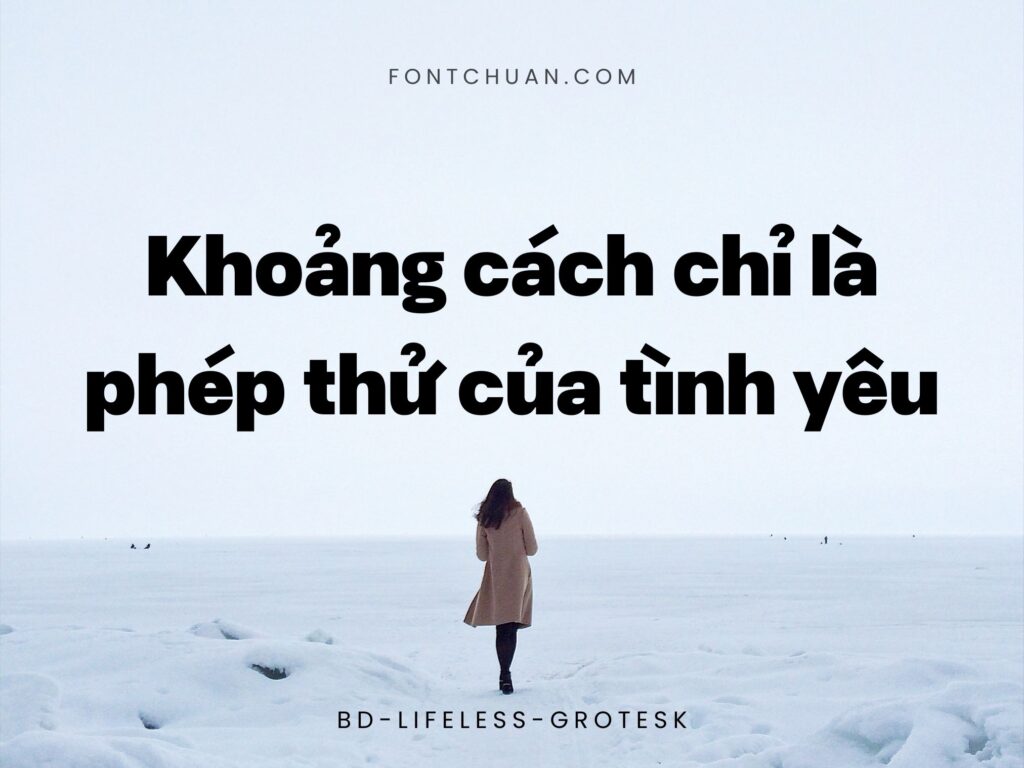
Font Bd Lifeless Grotesk Font Tiếng Việt
Tác giả Font: Harry Dinh
BD Lifeless Grotesk là một font sans-serif được thiết kế bởi Harry Dinh, nhằm tạo ra một kiểu chữ trung tính và đơn giản, phù hợp cho nhiều mục đích sử dụng khác nhau. Font này bao gồm 9 trọng lượng từ Thin đến Black và hỗ trợ nhiều ngôn ngữ Latin, bao gồm cả tiếng Việt. BD Lifeless Grotesk được phát hành miễn phí cho cả mục đích cá nhân và thương mại, với yêu cầu ghi công tác giả. Font được sưu tầm và đăng bởi thành viên của Font Chuẩn.
Font có thiết kế chữ đơn giản, các đường nét rõ ràng và cân đối, tạo nên sự dễ đọc và hiện đại. BD Lifeless Grotesk phù hợp cho các thiết kế liên quan đến thương hiệu, tiêu đề, poster và các ấn phẩm truyền thông cần sự chuyên nghiệp và tinh tế. Các ngành nghề như quảng cáo, bất động sản, giáo dục và công nghệ có thể tận dụng hiệu quả font này. Ngoài ra, BD Lifeless Grotesk cũng thích hợp cho các sự kiện như lễ hội, sinh nhật, ngày Nhà giáo và Valentine.